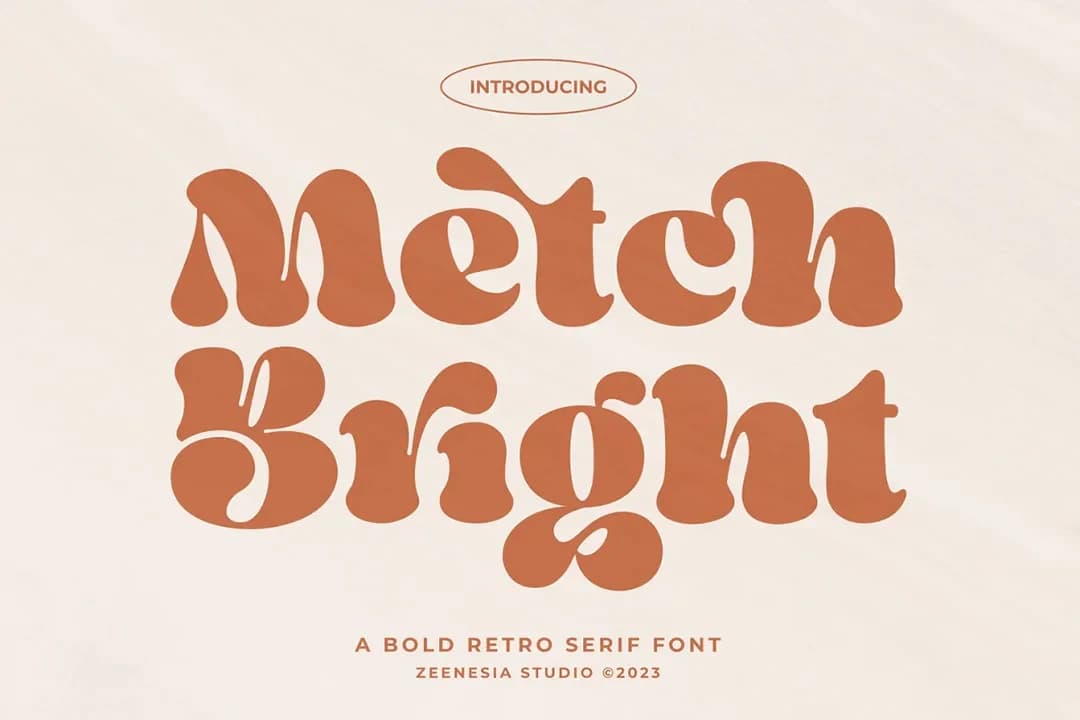
Metch Bright – A Retro Bold Font
Metch Bright Font, temiz ve şık bir şekle sahip çok yönlü bir retro serif yazı tipidir. Genel tipografi, harfler arasında düzen ve uyum sağlamak için güçlüdür. Net ve kalın bir görünüme sahip modern ve klasik bir serif yazı tipidir. Büyük boyutlarda da çok yönlü bir fonttur ve harika çalışır.
Metch Bright Font temiz, şık bir şekle sahip çok yönlü bir retro serif yazı tipidir. Genel tipografi, harfler arasında düzen ve uyum sağlamak için güçlüdür. Net ve kalın bir görünüm sunan modern ve klasik bir serif yazı tipidir. Büyük boyutlarda da çok yönlü ve harika çalışır.
Editoryal projeler, marka kimliği, logo tasarımı, web fontu, giyim markalama, ürün ambalajı, dergi başlıkları için mükemmeldir veya herhangi bir arka plana şık bir metin katmanı olarak da kullanılabilir.